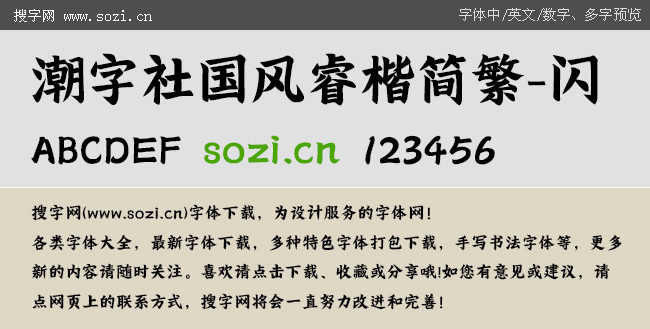
潮字社國風睿楷簡繁-閃
搜字網提供一款潮字社國風睿楷簡繁-閃中文字體下載,潮字社國風睿楷簡繁是一款毛筆書法藝術字體,參考了古代書法楷書的結構與筆畫形態,融合了榜書正氣、學深的氣質。字形流暢自然,渾厚有力,適合應用于藝術設計、平面宣傳設計、網頁設計等領域等應用。(本字體為個人非商用版,商用請聯系作者購買授權)